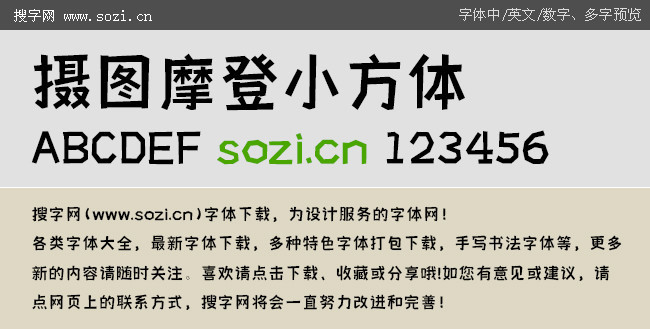
攝圖摩登小方體
搜字網(wǎng)給大家提供一款攝圖摩登小方體中文字體下載,攝圖摩登小方體字體的設(shè)計(jì)靈感來(lái)自對(duì)未來(lái)空間的想象,傳達(dá)給人一種未來(lái)與現(xiàn)實(shí)的交際感。筆畫(huà)方正質(zhì)樸而又不失靈氣活力,適中的字體筆畫(huà)粗度和幾何感的細(xì)節(jié)設(shè)計(jì),讓字體有良好的視覺(jué)應(yīng)用表現(xiàn)。